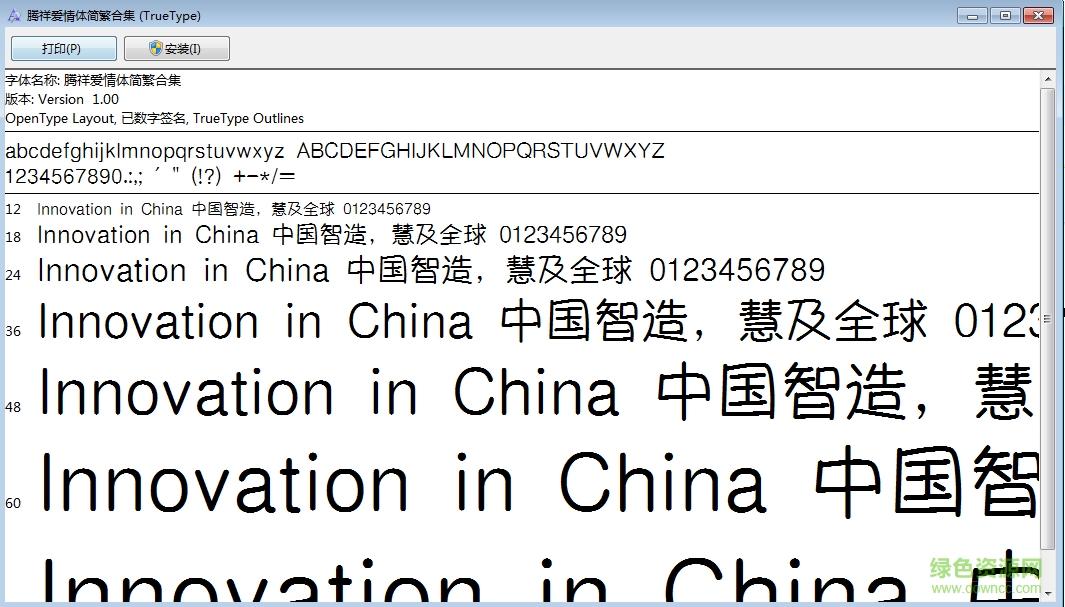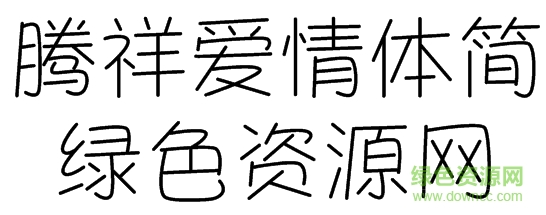
騰祥愛(ài)情體簡(jiǎn)繁合集
騰祥愛(ài)情體是一款字跡輕柔溫和的騰祥字體,簡(jiǎn)潔端正的字形讓人感受愛(ài)情的美好,快來(lái)綠色資源網(wǎng)寫(xiě)一封書(shū)信或制作一張海報(bào)吧!
騰祥愛(ài)情體簡(jiǎn)字體介紹
此款字體是由設(shè)計(jì)師孔淼手繪完成每個(gè)字形的原稿,再由騰祥公司調(diào)整修改完成的美術(shù)體字庫(kù)。一共有兩款粗細(xì),本款為愛(ài)情體細(xì)。當(dāng)春三月,微風(fēng)輕拂,綿綿細(xì)雨,柳條輕搖,在這萬(wàn)物復(fù)蘇的季節(jié)“騰祥愛(ài)情體”生長(zhǎng)了。一款筆畫(huà)輕松、結(jié)構(gòu)疏緩的字體,使文字表達(dá)更加貼心與無(wú)微不至。本款字閱讀流暢、筆畫(huà)舒展富于朝氣與生機(jī)?!靶那榫拖耧L(fēng)一樣自由,愛(ài)情就在不遠(yuǎn)處等著你”在這浪漫的季節(jié)期待您與“騰祥愛(ài)情體”的美好邂逅噢!
騰祥愛(ài)情體繁
騰祥愛(ài)情體是一款中文繁體和簡(jiǎn)體輸入的手寫(xiě)體,以筆畫(huà)纖柔、舒緩,是騰祥字庫(kù)今年全新推出的藝術(shù)字體,可適用于數(shù)字媒體、包裝設(shè)計(jì)、廣告設(shè)計(jì)、網(wǎng)頁(yè)設(shè)計(jì)等領(lǐng)域,編碼為GB2312-80。